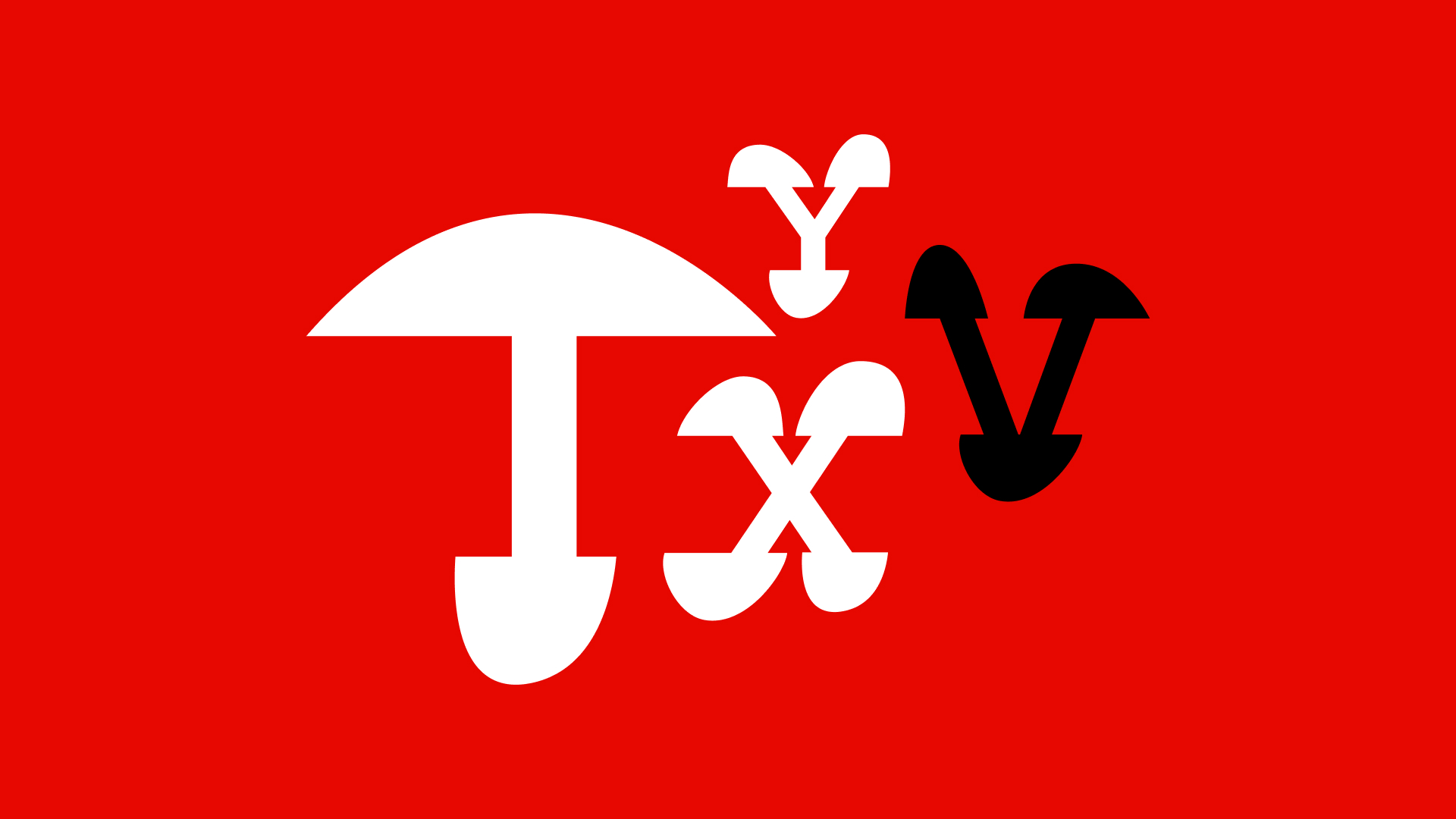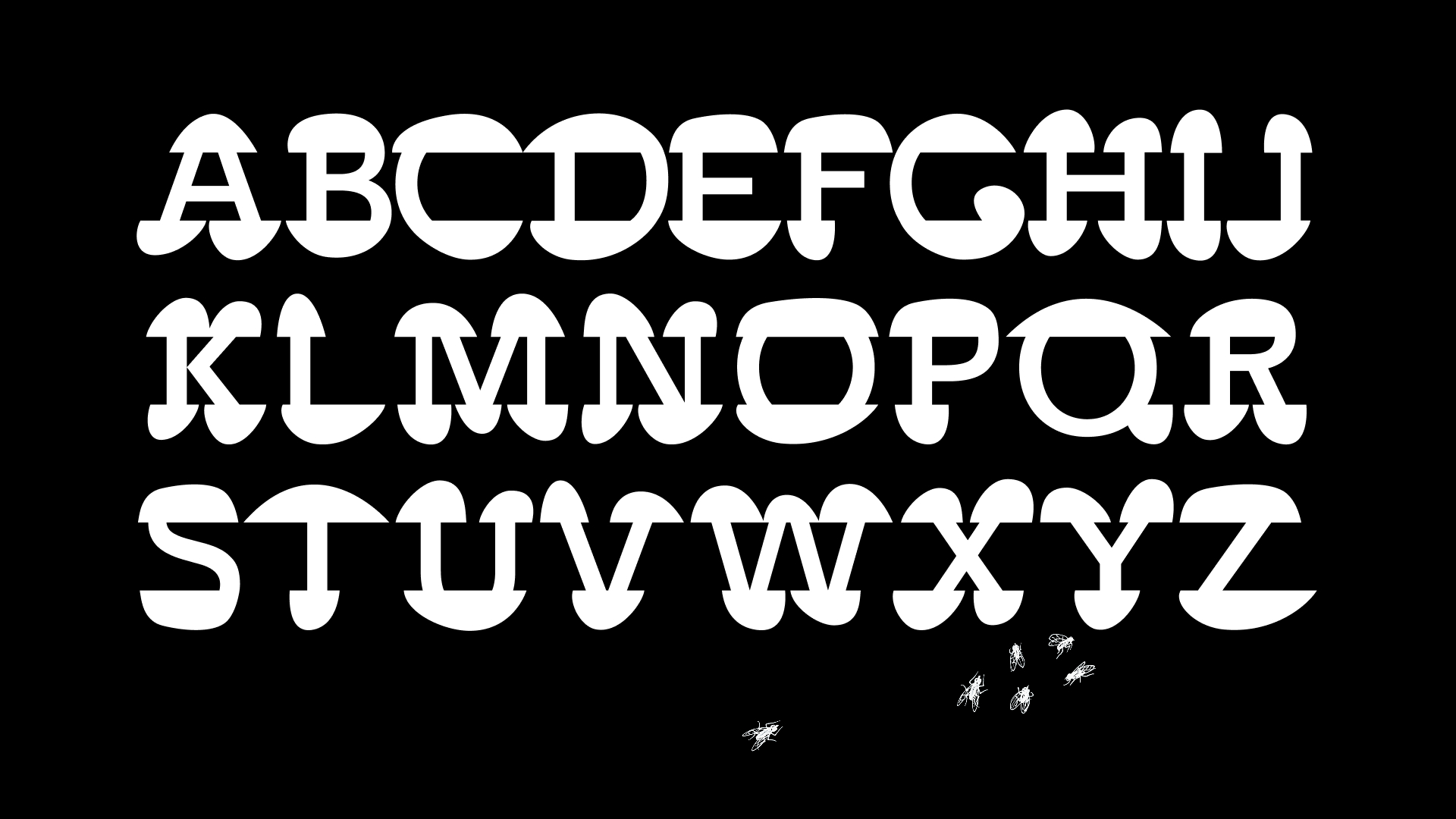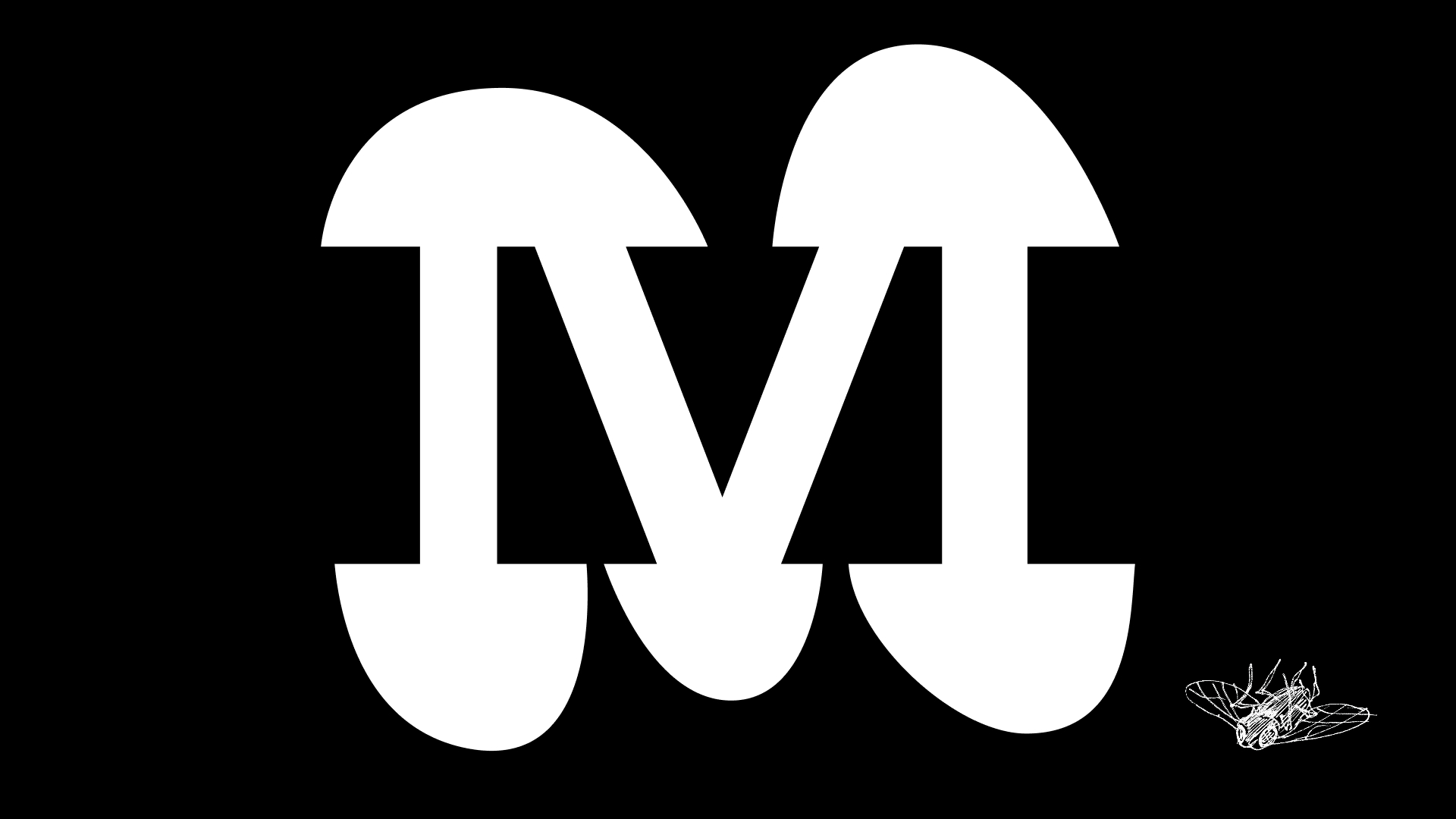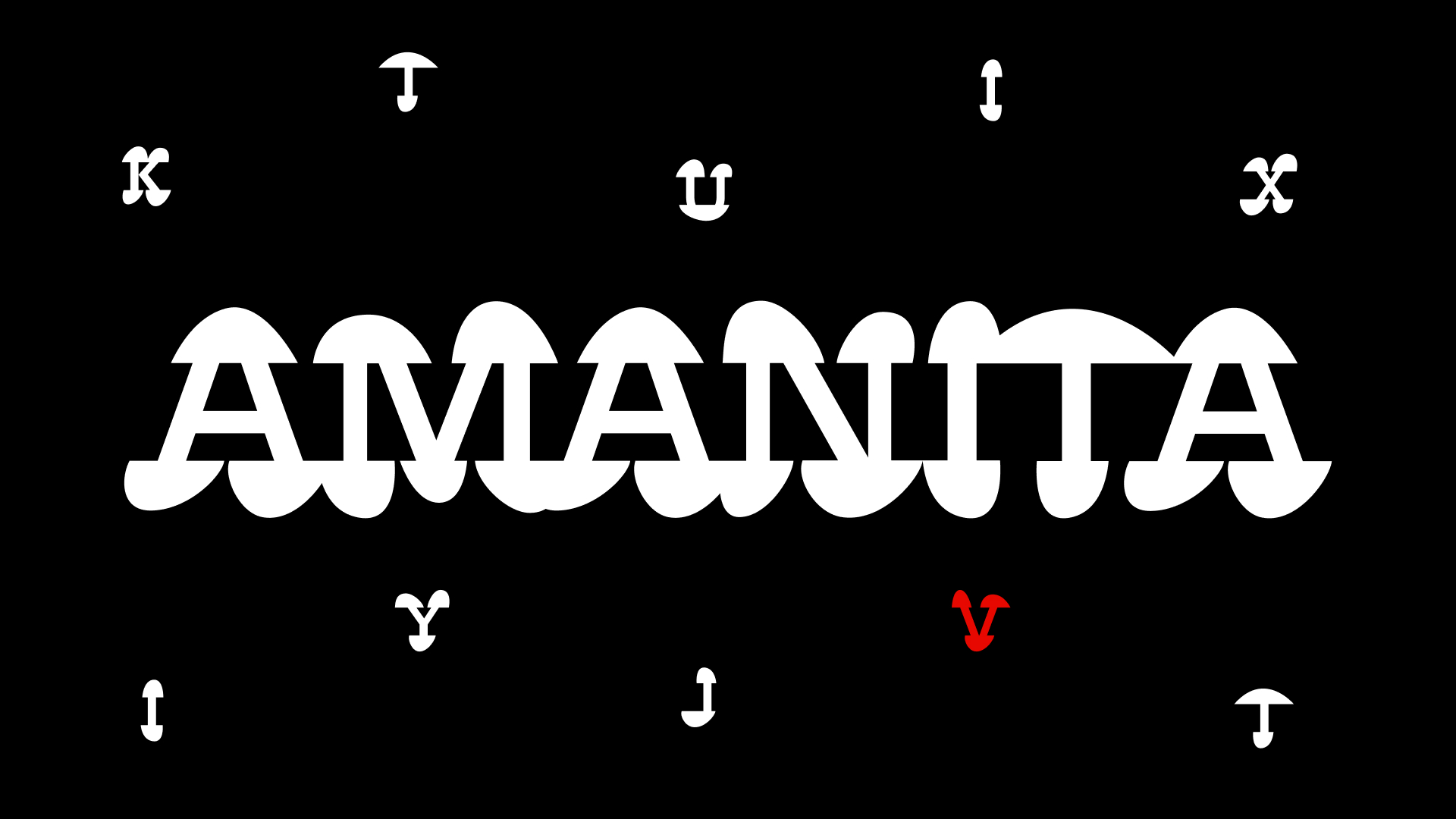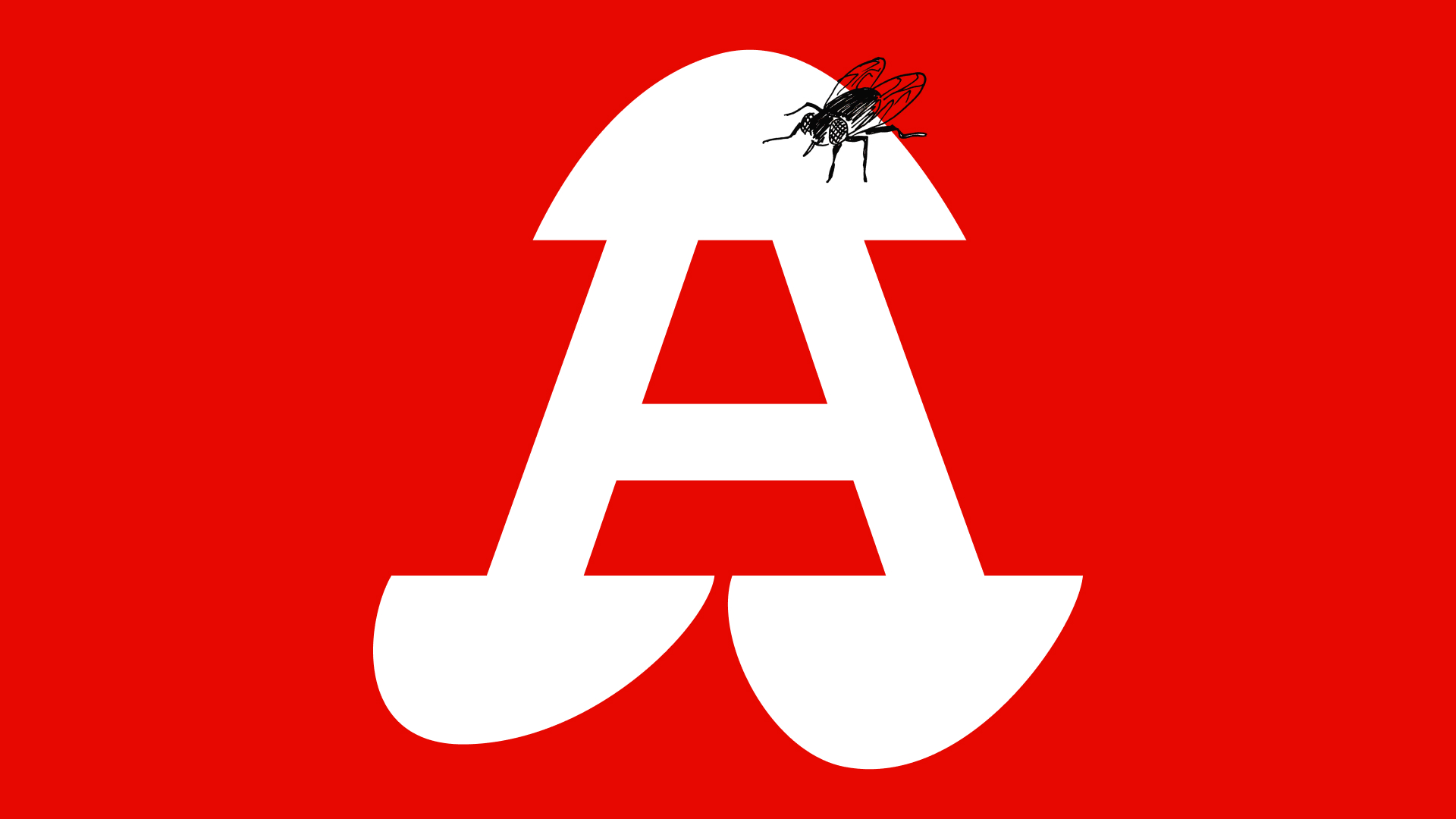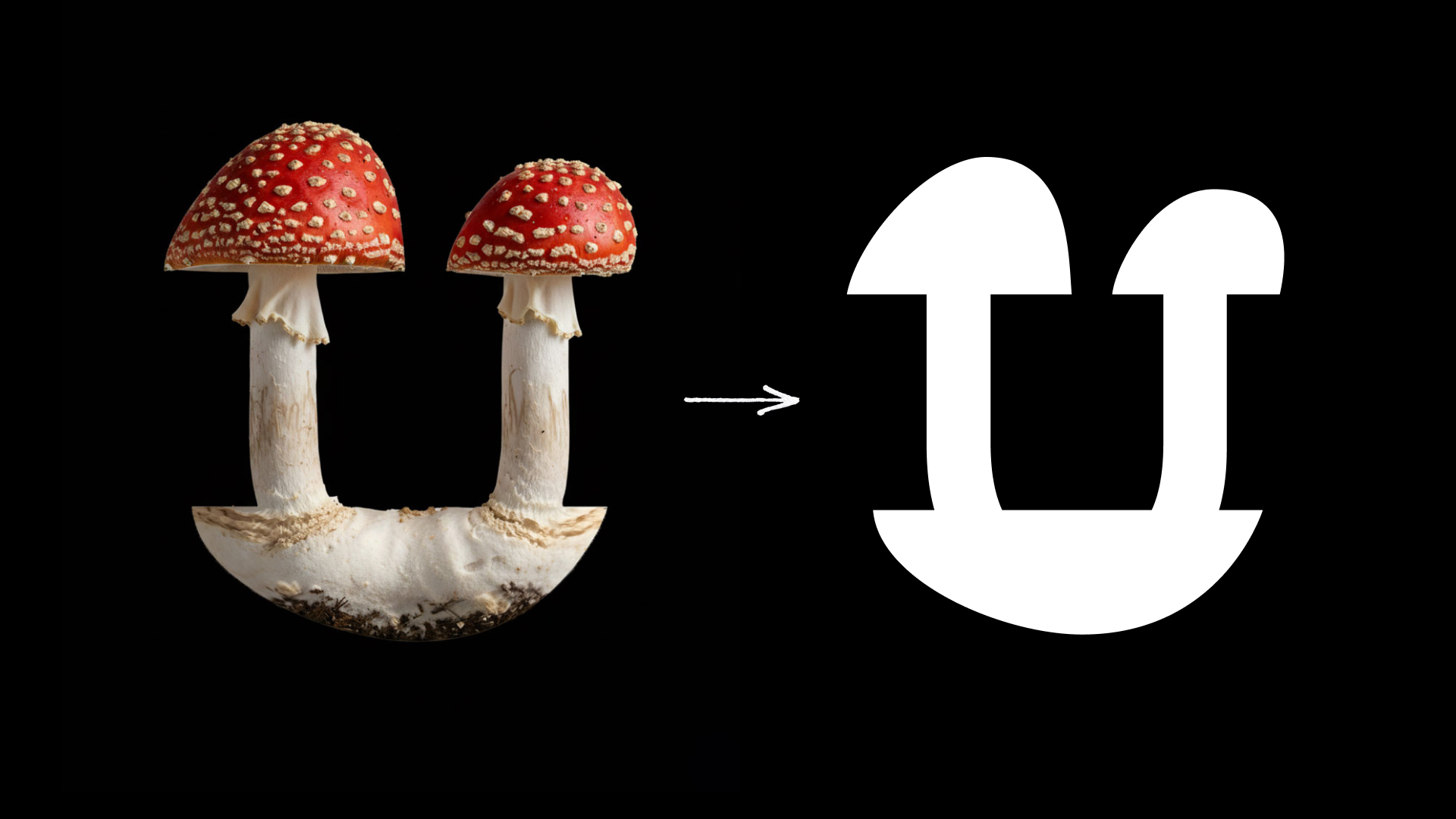
Экспериментальный шрифт
Шрифт Amanita
Amanita — брусковый акцидентный шрифт, вдохновлённый внешним видом мухомора Amanita muscaria, ярким и привлекающим внимание.
Шрифт Amanita — естественный по своей натуре, дуалистичный в своей неидеальности и чёткой геометрии центральной линии шрифта. Он создан для акцентных решений и подчеркнуто индивидуален. Современный, естественный, вдохновленный царством грибов — шрифт мимо которого невозможно пройти.